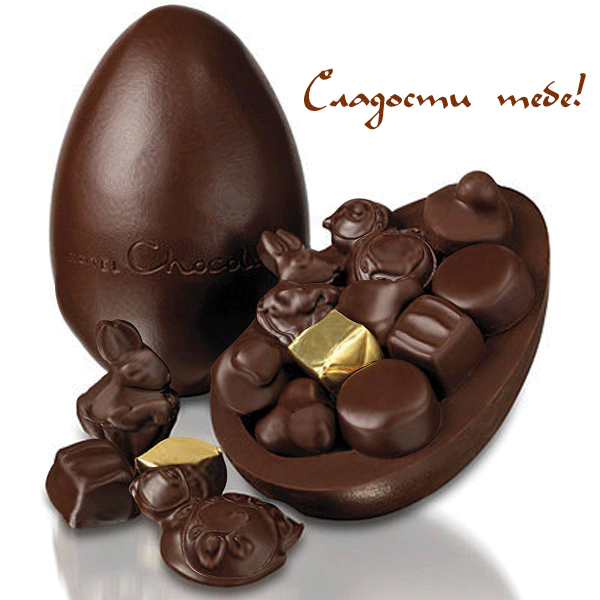
А как называется этот шрифт? Сегодня у нашего соотвечика Сашки день варенья, так давайте же поздравим.. . и пожелаем...
Шрифт калиграфический, а с Днем рождения ПОЗДРАВЛЯЮ!! !
Похож на Classica ,,,)))